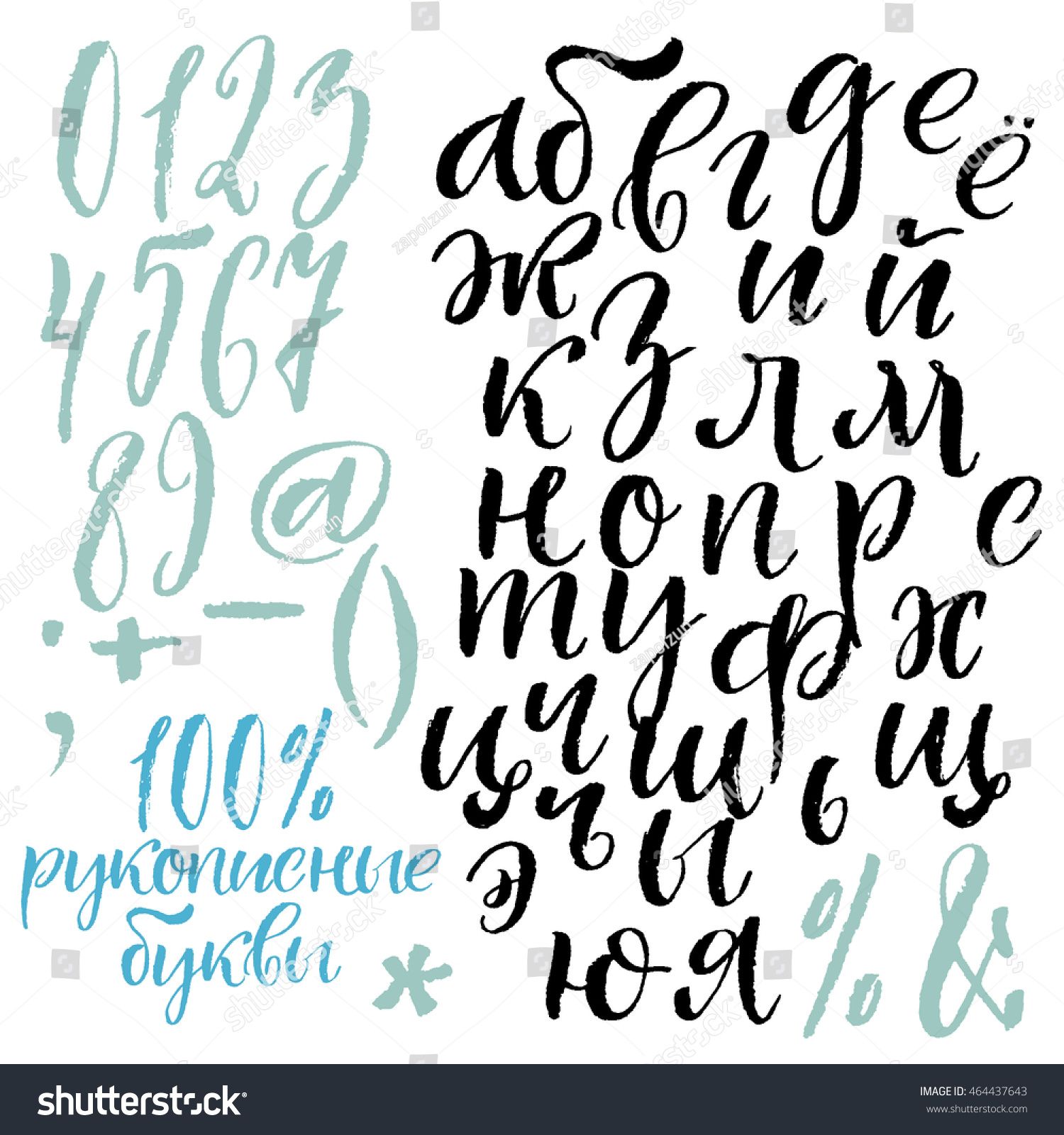
Онлайн прописи для письма. Буквы и цифры
Сейчас ни для кого не является секретом тот факт, что время на обучение ребенка правильному каллиграфическому письму в первом классе сведено к минимуму.
Успеть бы показать, как буква пишется и читается.
И от этой спешки неокрепшие пальчики ребенка начинают через некоторое время выводить такие каракули, что о написанном можно только догадываться.
Закрепить навык письма, выработать автоматическое правильное и что самое главное понятное написание письменных букв помогают дополнительные занятия с прописями.
На этой страничке вашему вниманию представлен онлайн-сервис по генерированию прописей, которые вы можете составить самостоятельно с учетом всех проблем и потребностей вашего ребенка.
Генератор прописей преобразует введенный вами текст в рукописные прописи, применяя специально созданный каллиграфический шрифт с пунктирной и сплошной линией.
Генератор прописей
Чтобы составить прописи, выберите на панели нужные вам функции.
Вид страницы: в косую линию, в узкую линию, в широкую линию.
Выбор страницы зависит от степени подготовленности вашего ребенка.
Для написания цифр используйте страницу в клетку.
Вид шрифта: пунктирный, сплошной серый, сплошной черный.
Для обводки букв выберете пунктирный шрифт или сплошной серый.
Для самостоятельного письма по примеру — сплошной черный.
Положение страницы: книжное, альбомное.
В отдельной строке напишите задание.
Например: обведи буквы, пропиши по образцу, пропиши самостоятельно по образцу и т.п.
Далее заполните форму текстом на свое усмотрение.
Это могут быть отдельные буквы, слоги, слова. Пропишите те буквы и слоги, при написании которых у вашего ребенка возникают трудности.
Вы можете вписать предложения или текст (стихотворение, загадку).
Для перехода на новую строку и корректного отображения текста используйте кнопку ENTER.
В книжном формате ширина строки порядка 40-42 знака, учитывая пробелы. В альбомном формате ширина строки порядка 55-58 знаков.
С помощью онлайн генератора прописей вы можете составить, скачать и распечатать задания для детей любой сложности.
Для дошкольного возраста используйте пунктирный шрифт и страницу с косой линией.
Пропишите отдельные строчные и заглавные буквы, слоги и слова для обводки.
Для первоклассников можно создать прописи уже со сплошной линией.
Вы можете написать по одному примеру, оставив строку пустой для самостоятельного письма.
Вы так же можете с помощью генератора прописей составить грамматическое упражнение для ребенка.
Напишите слова или текст с пропущенными буквами. Это могут быть словарные слова, слова с проверочными гласными, слова с приставками и т.п.
Не забудьте про цифры 🙂
Используйте страницу в клетку и пунктирный шрифт.
Можно распечатать не только прописи с цифрами, но и прописи с математическими примерами, составив их самостоятельно.
Надеюсь, что сервис по созданию прописей поможет вам в обучении ваших детей.
С помощью этого конвертера вы можете добавить любому тексту различные оригинальные эффекты: курсива, тени, объема, рукописного написания, готического стиля.
Обычно курсивное начертание текста формируется браузером или текстовым редактором по специальному алгоритму из обычного шрифта (TrueType). Такой шрифт представляет собой файл с координатами точек кривых для каждого символа, которые можно пересчитать для литеры любого размера (пункта). Пользователь отмечает или выделяет тем или иным способом (в зависимости от программы) участок текста (например, нажатием кнопки или специальным тегом), затем программа, используя выбранный пользователем шрифт, формирует его курсивное начертание, пересчитывая координаты кривых. Для всех программ алгоритм формирования курсива практически одинаковый и, как результат, курсивное начертание выглядит идентично.
В кодировку Уникод (UTF) в свое время были добавлены символы, имеющие изначально курсивное, рукописное, готическое и прочие художественные начертания.